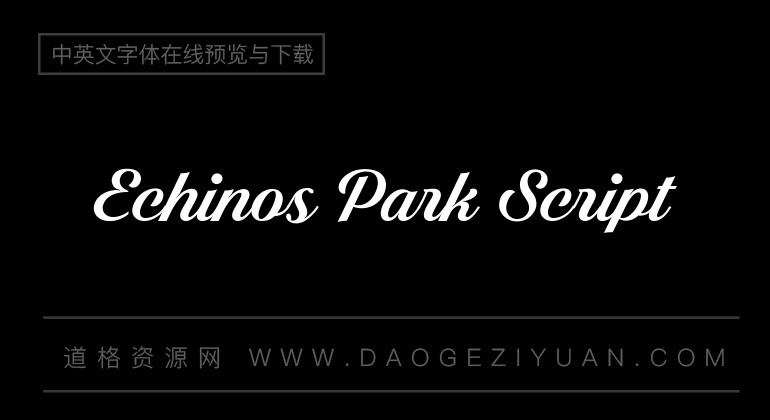
Echinos Park Script
Echinos Park Script 是一款具有精美外观的手写风格字体,它包含了大量的文本样式,可以用于设计各种海报,网页,卡片,书籍,商标等。它的字体特点是曲线流畅,笔画细腻,而且基本上没有重复的字形,这使得它在设计中显得非常独特而有趣。它还支持多种语言,可以使用它来设计中文,英文,日文,韩文,法文,西班牙文,德文,意大利文等等。另外,它的字符集也非常丰富,可以满足不同的设计需求。
Echinos Park Script是一款非常不错的手写艺术字体,具有很好的视觉感,适合于文化类的宣传设计、商业类品牌的广告和产品包装设计以及个性化文字排版等较多场景。